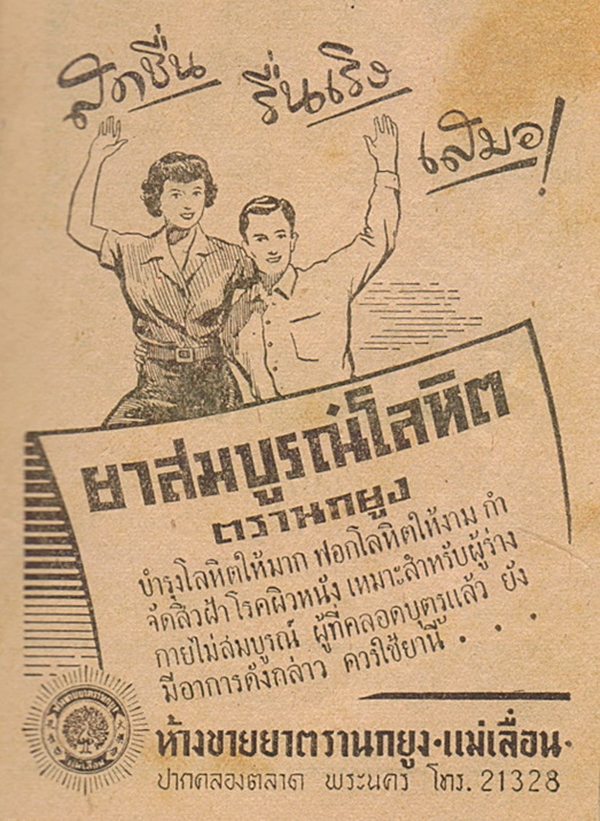
ขอเรียนถามเรื่องตัวหนังสือแบบนี้
ขอเรียนถามเรื่องตัวหนังสือแบบนี้ เขาเรียกชื่อว่าอะไรครับ ผมชอบ..อยากหามาใช้แต่งภาพบ้างใน cs6 แต่ผมไม่รู้จักชื่อเรียกตัวหนังสือแบบนี้และไม่ทราบว่าจะหามาใช้ได้จากแหล่งใดบ้างครับ
ถ้าจัดกลุ่มก็น่าจะเรียกได้ว่า ฟอนต์ใน "ใบปิดโฆษณา" ครับ
ส่วนกลุ่มที่ทำฟอนต์ลักษณะนี้มากที่สุดก็น่าจะเป็น เซียมไท้ ครับ
เหมาะกับธีมย้อนยุค